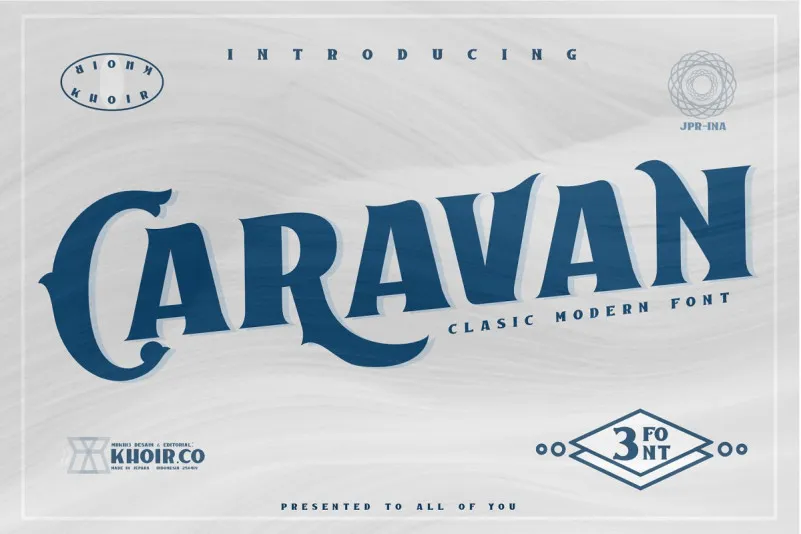
Caravan Display Font – Download Grátis
Introduzimos a Caravan Font para vocês neste design exclusivo criado pelo designer Khoir. Esta é uma fonte premium disponível na Creativemarket e agora, nesta oferta especial, está disponível de forma gratuita para download. Caravan é uma combinação perfeita de elegância clássica e estilo moderno, projetada para deixar um impressionante impacto em cada letra. Ela se beneficia de seu design versátil, que mescla o charme antigo e retro com a simplicidade e originalidade modernas. Caravan é uma fonte rica em características, onde você sempre terá alternativas interessantes para personalizar as letras. Além disso, adicionamos um elemento divertido: ilustrações românticas que irão te levar de volta ao seu estado mais jovem, ajudando a transformar o design conforme você desenhar. É hora de dar vida à sua arte com esta fonte. Vai ser uma experiência imersiva e incrível para qualquer projeto que você estiver desenvolvendo. Não se esqueça de deixar seus clientes ou usuários impressionados enquanto mantém um toque moderno em cada letra, dando vida ao seu design único.